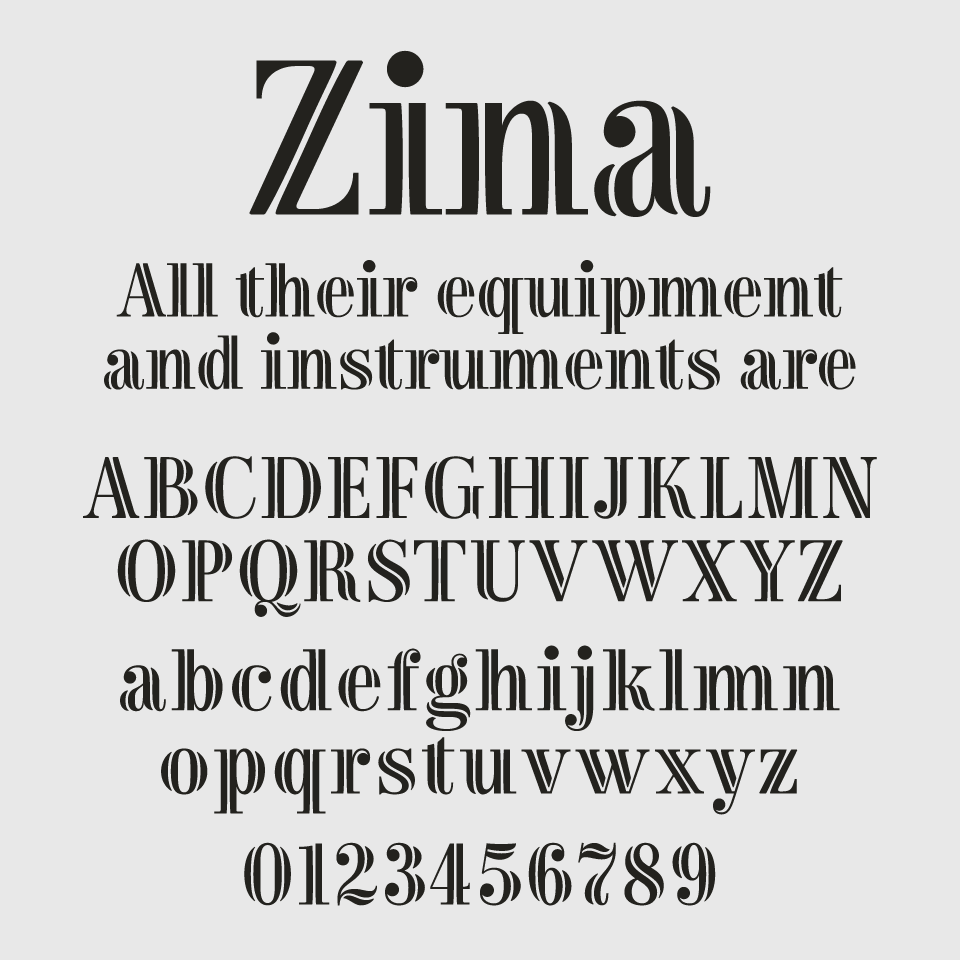
Zimaフォントは、縦長の構造にコントラストの強いシェーディングを加えた、装飾性の高いディスプレイセリフです。
ストロークの一部に2重になっており、縞模様のような飾りにも見える、クラシカルだけど、可愛らしい雰囲気を感じられるフォントです。
華やかさと格式を兼ね備えたこのフォントは、アート系のポスターや装丁デザイン、イベントタイトルなどで個性を引き出すのに最適です。1文字1文字にアクセントがあるため、短いワードやタイトルなどに特に向いています。